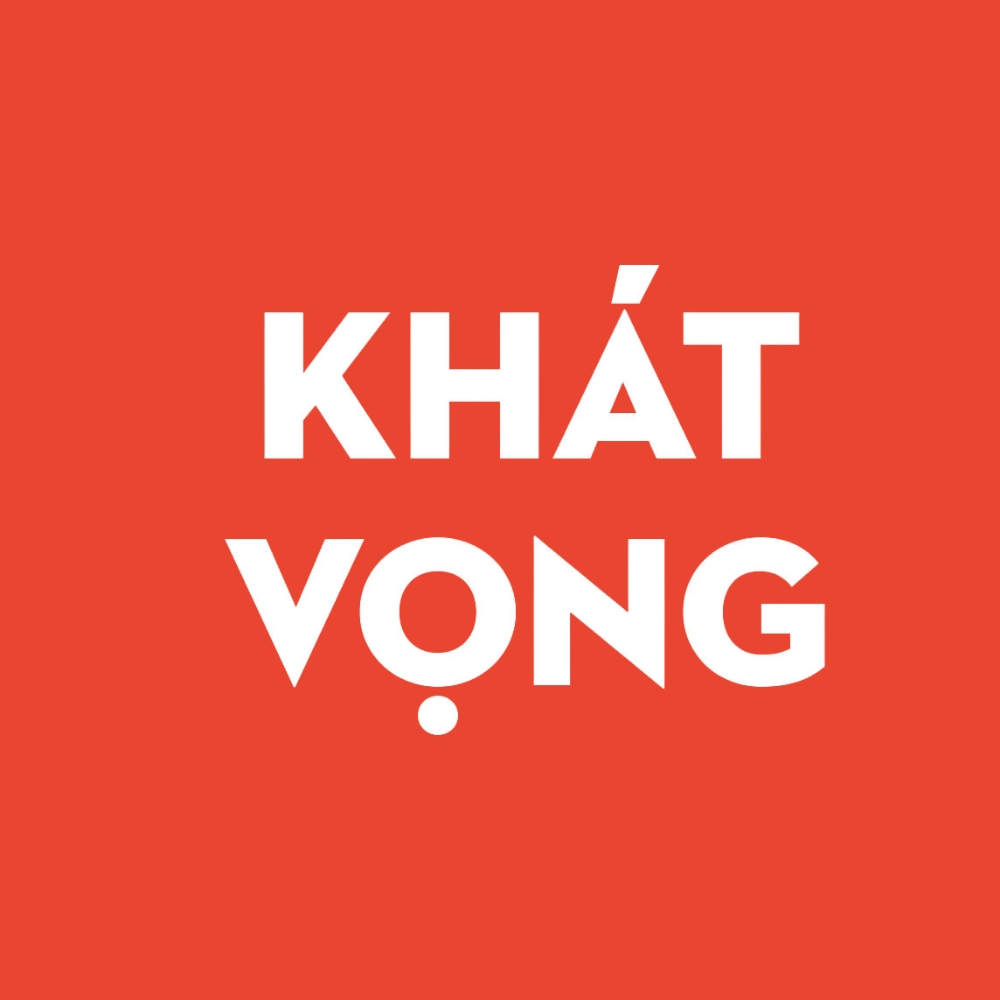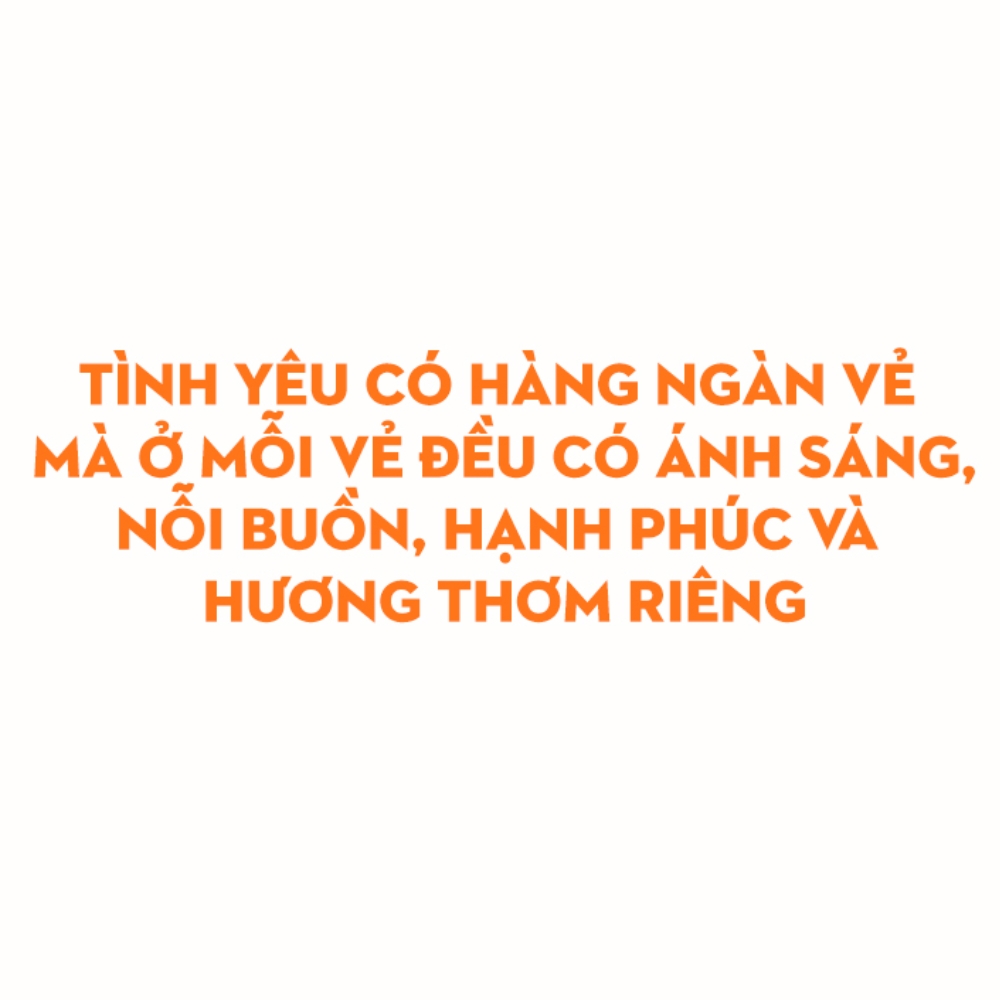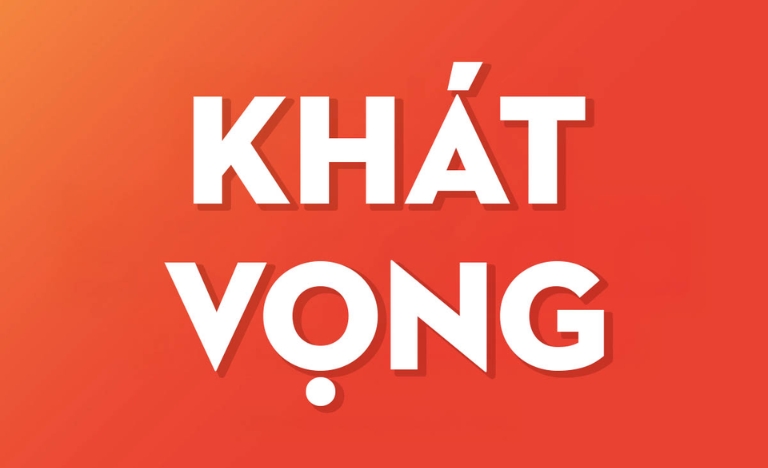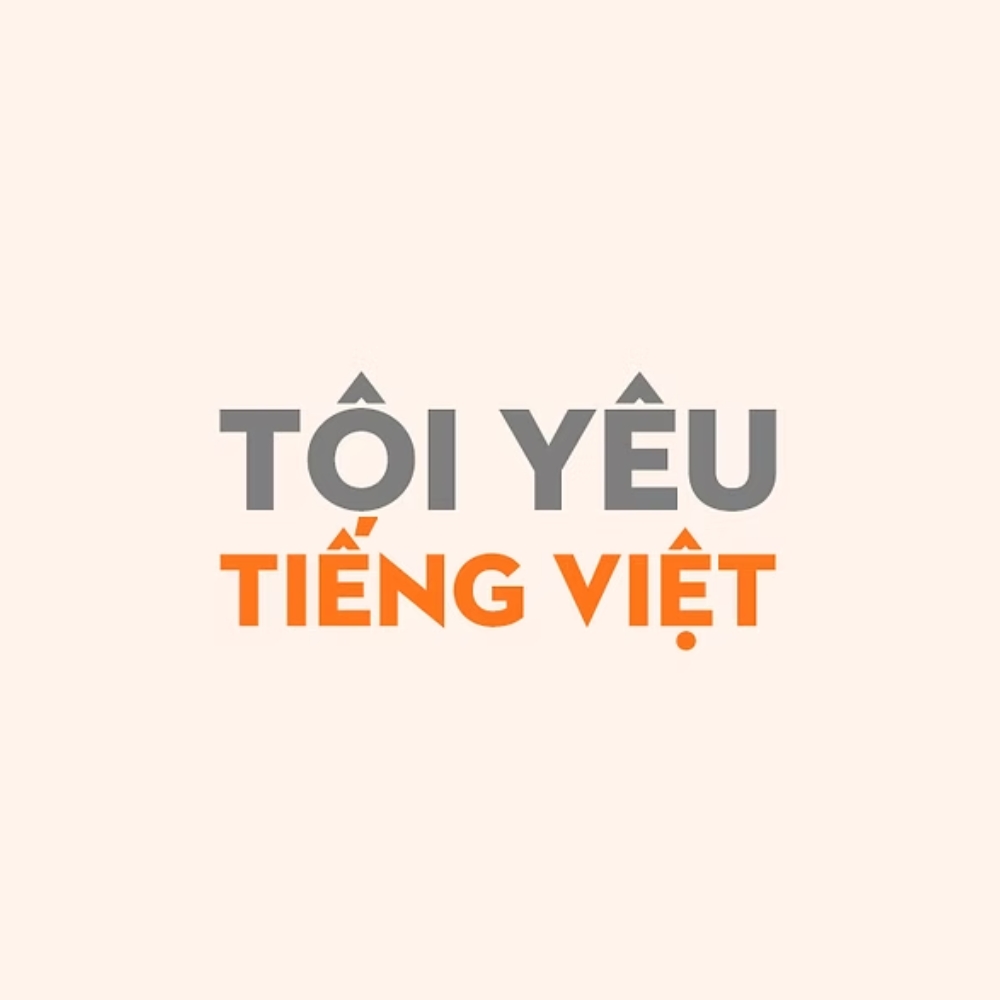
Neutraface 2 là một bộ font chữ Sans Serif mang tính biểu tượng, được lấy cảm hứng từ phong cách thiết kế hình học của kiến trúc sư lừng danh Richard Neutra. Với sự cân bằng giữa nét cổ điển và tinh thần hiện đại, bộ font Việt hóa SVN Neutraface 2 đã trở thành lựa chọn phổ biến cho các dự án yêu cầu sự tinh tế, minh bạch và chuyên nghiệp.
Đặc điểm nhận diện và tính thẩm mỹ của font Việt hóa SVN Neutraface 2
Dòng font này sở hữu cấu trúc hình học chuẩn xác với các đường nét dứt khoát và khoảng cách ký tự được tính toán khoa học. Điểm đặc biệt của SVN Neutraface 2 nằm ở độ cao của các ký tự vừa phải kết hợp với những đường bo góc sắc sảo, gợi liên tưởng đến các bản vẽ kiến trúc Art Deco thời kỳ giữa thế kỷ 20.
Sự tinh tế của Neutraface 2 còn được thể hiện qua khả năng thích ứng linh hoạt với nhiều phong cách khác nhau. Dù được sử dụng cho các tiêu đề lớn hay các dòng ghi chú chi tiết, font chữ này luôn duy trì được sự rõ ràng và sức hút thị giác ổn định. Đây là giải pháp phù hợp để truyền tải những giá trị về sự chuyên nghiệp, bền vững và tư duy thiết kế hiện đại trong từng sản phẩm đồ họa và kiến trúc.
Bộ font này bao gồm nhiều biến thể từ nét mảnh đến nét dày, giúp bạn dễ dàng tạo ra sự phân cấp thông tin trong bản thiết kế. Dưới đây là bảng thông số chi tiết để bạn tham khảo trước khi cài đặt.
| Phân loại phong cách | Geometric Sans Serif / Architectural |
| Số lượng biến thể | Đầy đủ các cấp độ từ Light đến Bold |
| Mục đích phù hợp | Branding, Bản vẽ CAD, Website, Poster |
Gợi ý phối hợp: SVN Neutraface 2 mang tính hình học rất cao. Để tạo nên một bố cục hài hòa, bạn nên kết hợp font này với một kiểu chữ Serif mảnh cho phần nội dung thuyết minh dài hoặc giữ nguyên tinh thần tối giản bằng cách phối hợp giữa các độ đậm nhạt khác nhau trong chính gia đình font Neutraface.
03 Ứng dụng font Việt hóa SVN Neutraface 2 trong đời sống
Nhờ vẻ ngoài mang tính kiến trúc rõ rệt, bộ font chữ này mang lại giá trị thực tế cao khi được đưa vào thực tế trang trí và quảng bá các công trình hiện đại:
- Bảng hiệu và số nhà cho Homestay hiện đại: Những đường nét vuông vức của Neutraface 2 rất ăn ý khi được cắt laser trên vật liệu kim loại hoặc mica. Đối với các dự án nhà lắp ghép, văn phòng container, font chữ này giúp nâng cao vẻ ngoài chuyên nghiệp và hiện đại cho công trình.
- Thiết kế hồ sơ năng lực kiến trúc: Sử dụng Neutraface 2 cho các tiêu đề chương và thông số kỹ thuật giúp hồ sơ của bạn trông mạch lạc, dễ đọc và thể hiện gu thẩm mỹ tinh tế của người lập bản vẽ.
- Giao diện website giới thiệu dự án: Đây là một trong những font chữ hiển thị ổn định trên môi trường kỹ thuật số, giúp khách hàng dễ dàng tiếp cận các thông tin về giải pháp thi công và dịch vụ xây dựng một cách chuyên nghiệp.
03 Lưu ý khi sử dụng font Việt hóa SVN Neutraface 2 trong bố cục
Để khai thác hiệu quả vẻ đẹp của dòng font Sans Serif cao cấp này mà không làm ảnh hưởng đến thẩm mỹ chung, người thiết kế nên lưu tâm một số điểm sau:
- Kiểm soát khoảng cách dòng: Neutraface 2 có các nét ký tự khá thoáng, bạn nên nới rộng khoảng cách giữa các dòng một chút để văn bản không bị bết dính, giúp người đọc cảm thấy thư giãn hơn khi tiếp nhận thông tin.
- Lựa chọn độ đậm (Weight) phù hợp: Với các tiêu đề chính, hãy ưu tiên các kiểu Bold để tạo sự vững chãi. Với các đoạn ghi chú nhỏ trên bản vẽ CAD, kiểu Regular hoặc Light sẽ giúp bản vẽ trông thanh thoát và chuyên nghiệp hơn.